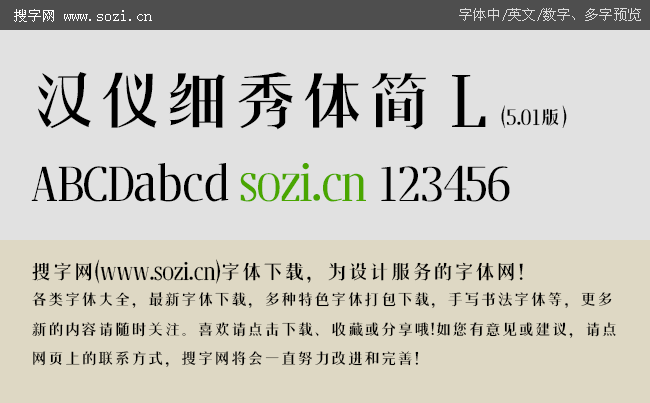
漢儀細秀體簡L
搜字網給大家提供一款漢儀細秀體簡L中文字體下載。漢儀秀體字形結構穩定,配合設計簡潔的筆畫,排版時整體線性效果更加突出,使閱讀更加流暢。 筆畫風格上融合了黑體與宋體的特征,線條簡潔,氣質圓柔、秀美,風格靈動、時尚。筆畫間的相互呼應更使得字體整體結構統一完整、避免了結構的呆板、生硬。可應用于平面設計、出版印刷、廣告設計、包裝設計等領域。